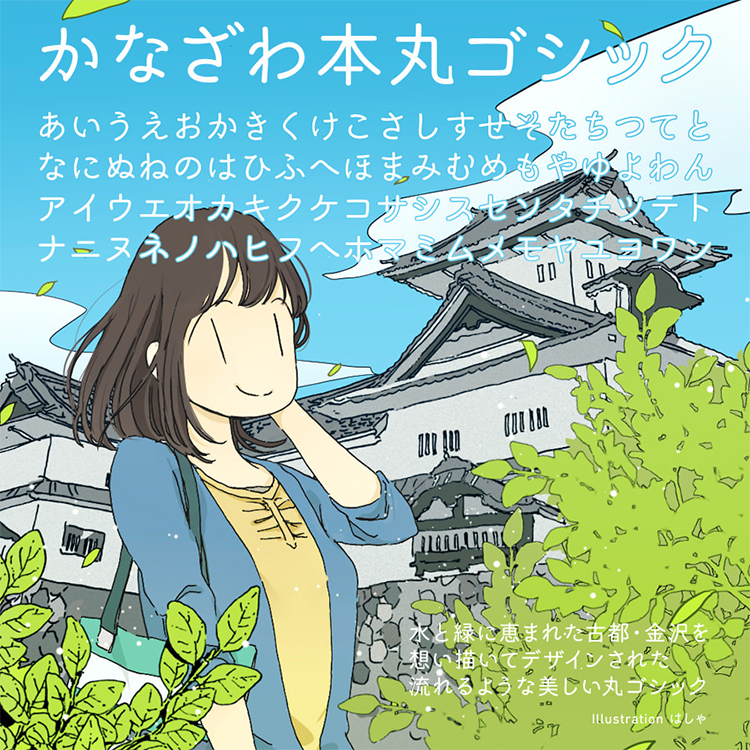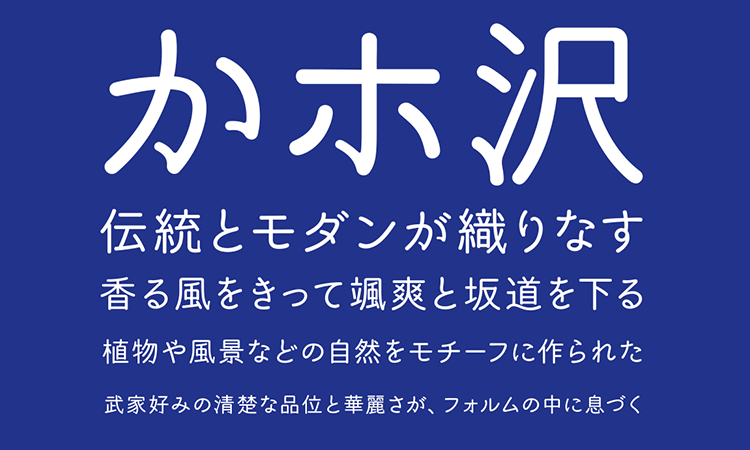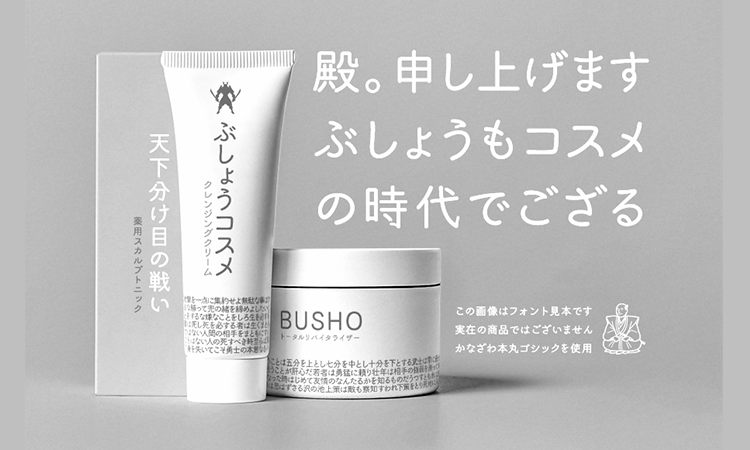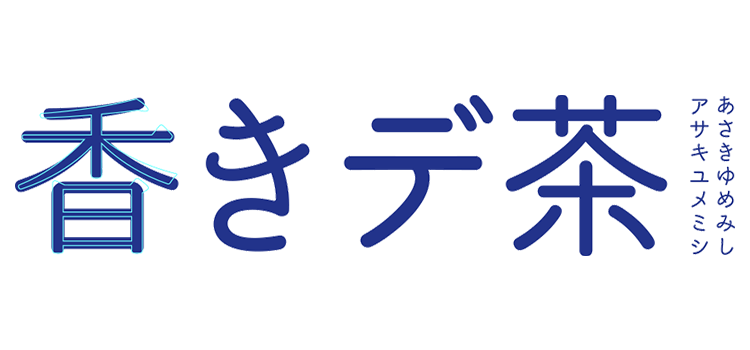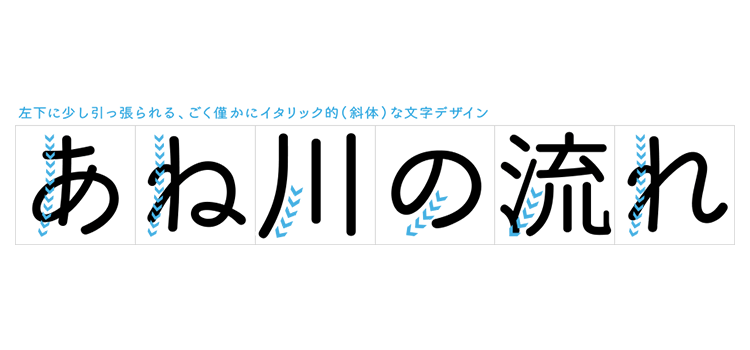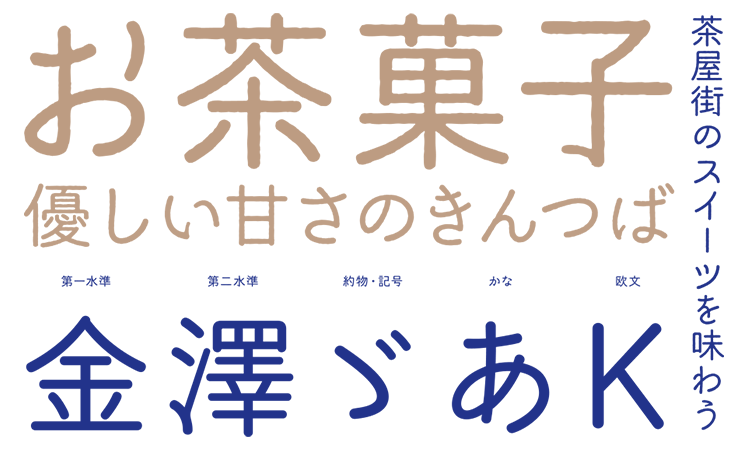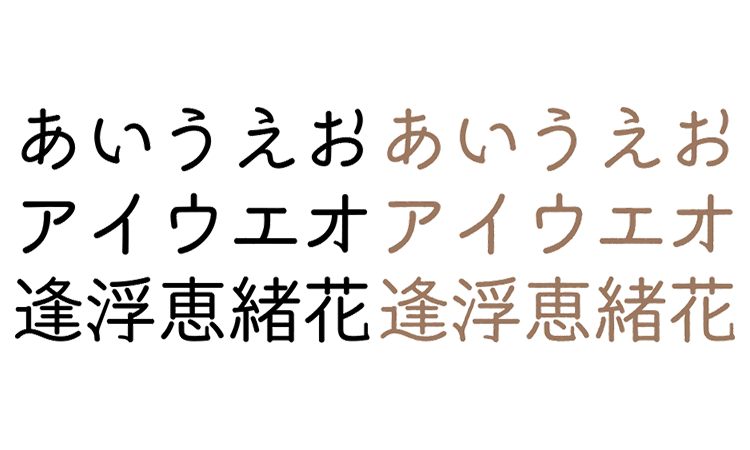
かなざわ本丸ゴシックは、気品と躍動感を備えた丸ゴシック体のフォントです。金沢城のある、自然豊かな金沢の街をイメージして作成されています。クラシックな柔らかさとキレのある表現が特徴です。
かなざわ本丸ゴシックの特徴
通常の丸ゴシック体のフォントと比べて、緩急のある大胆な動きのフォントに仕上がっています。明朝体の骨格がベースとなっており、モダンなデザインの中に、オールドスタイルの味わいある雰囲気が隠れています。全体的に左下に少し引っ張られたフォルムで、わずかにイタリック(斜体)の文字デザインになっています。
製品版のサンプル
かなざわ本丸ゴシック(レギュラー)、かなざわ本丸ゴシック茶菓子(ラフ)のサンプル
フリーフォントの「かなざわ本丸ゴシックmini」と製品版の「かなざわ本丸ゴシック」があります。
製品版は、第一水準の漢字2965字と第二水準のよく使う漢字460字、記号類・約物・キリル文字・半角カタカナ等647字が含まれています。フリーフォントとは異なり、縦書きも可能になっています。また、TrueTypeも梱包されています。さらに、おまけ特典としてまるがめ「かなざわ本丸ゴシック茶菓子」が付属しています。かなざわ本丸ゴシック茶菓子は、線が細かくガタガタとしている手書きのような味わいがあるフォントです。